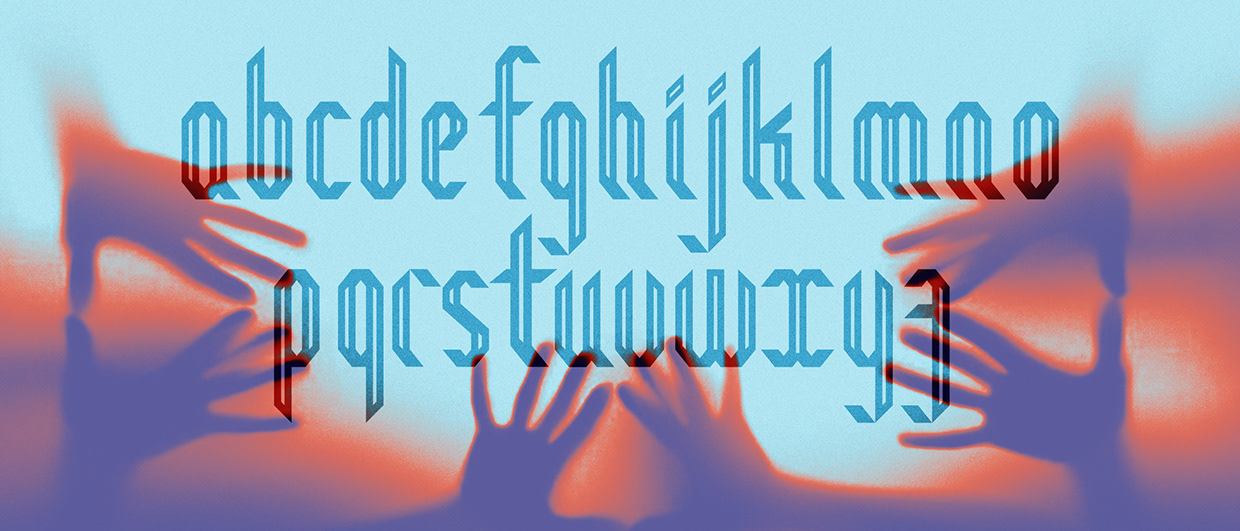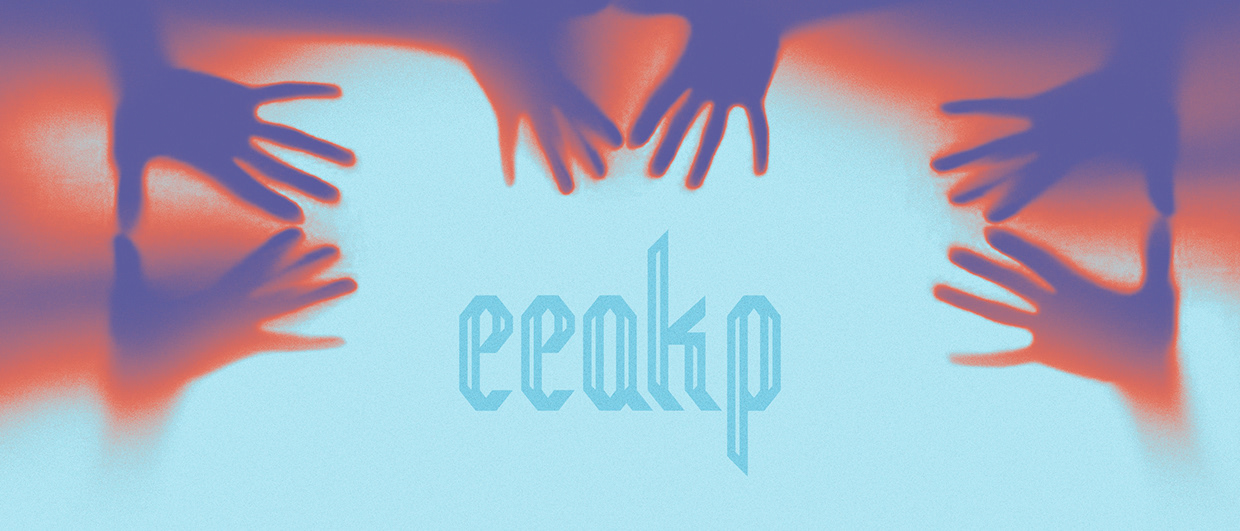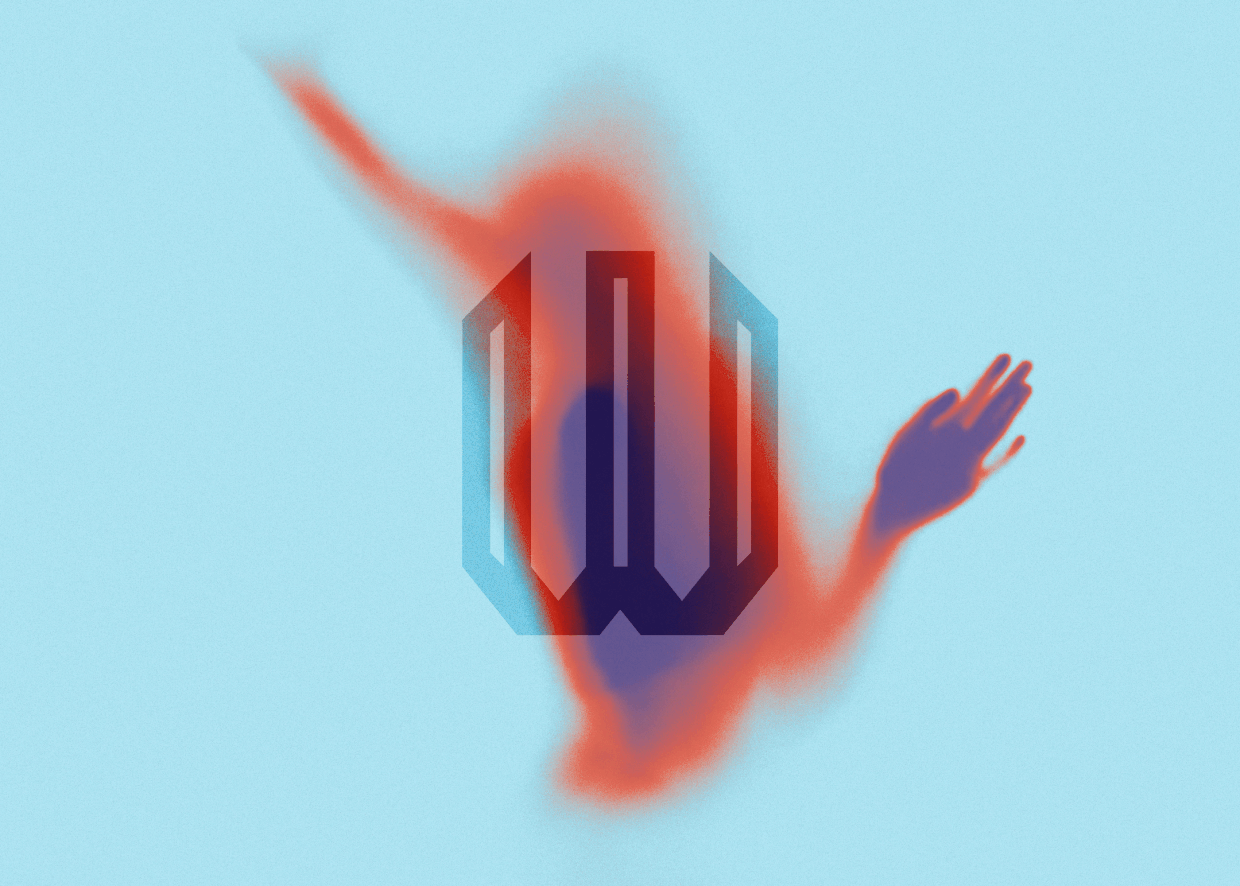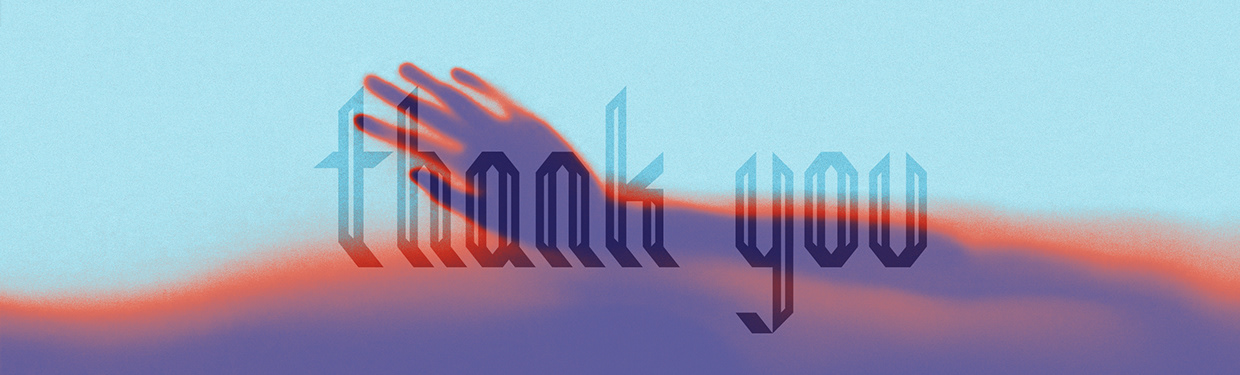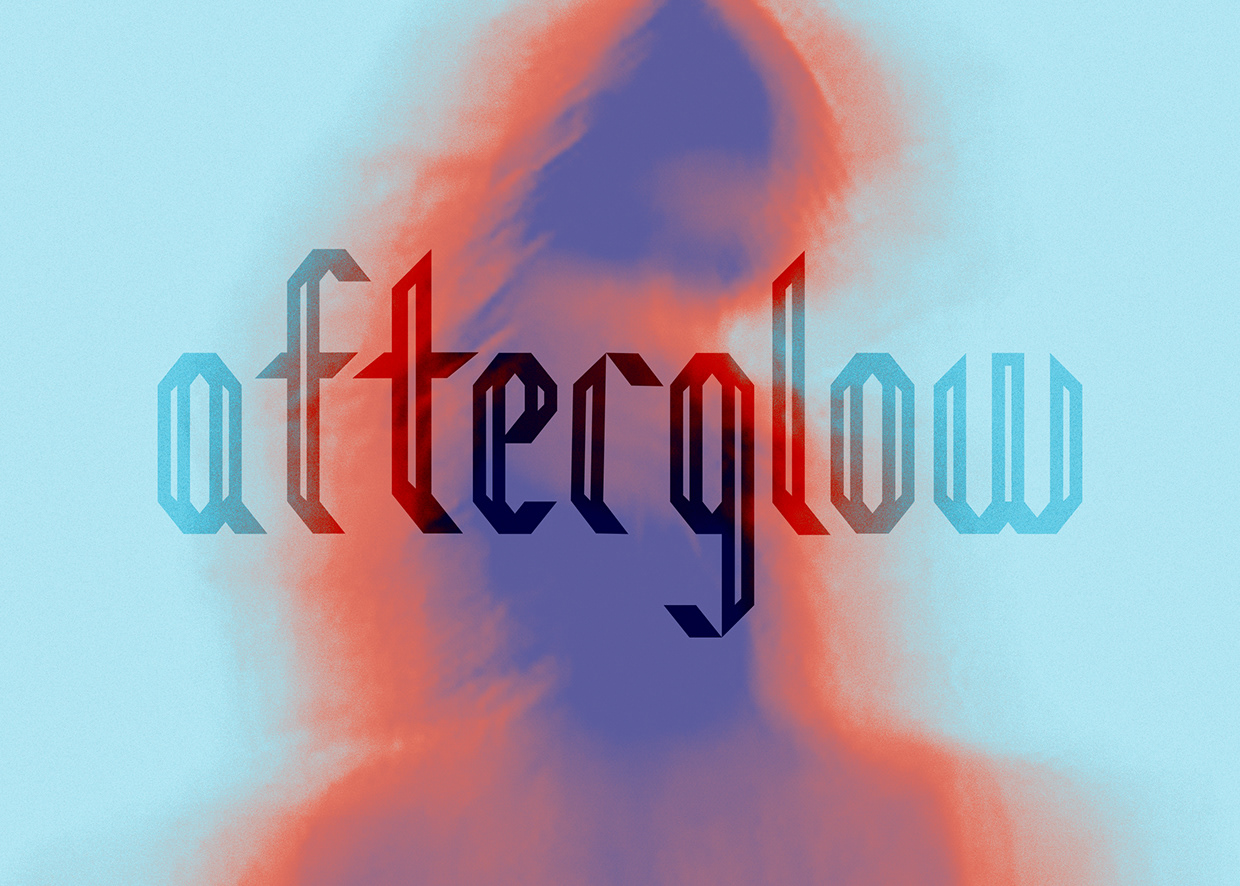
Afterglow - Simplified Gothic Typeface
[FR] Afterglow est une typographie expérimentale inspirée des formes gothiques modernes, construite avec des traits angulaires et une structure très minimaliste. Ce projet étudiant explore la façon dont une lettre peut garder son essence tout en étant réduite à des lignes simples et sculpturales. [EN] Afterglow is an experimental typeface inspired by modern gothic shapes, built with angular strokes and a very minimal structure. This student project explores how a letter can keep its essence while being reduced to simple and sculptural lines.